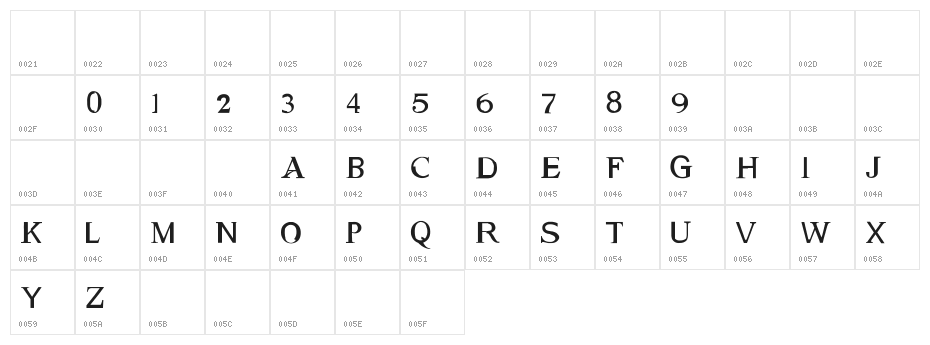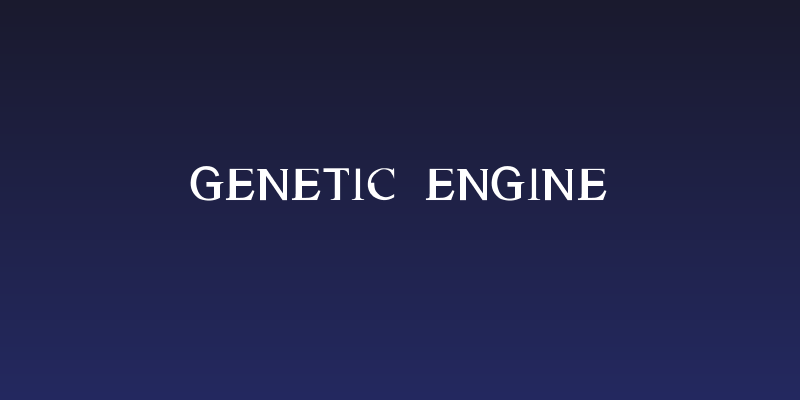
Genetic Engine Font
| Область применения | Logos, Headlines, Digital interfaces |
| Рекомендуемые проекты | Ideal for digital art, tech company logos, video game interfaces, and futuristic branding. |